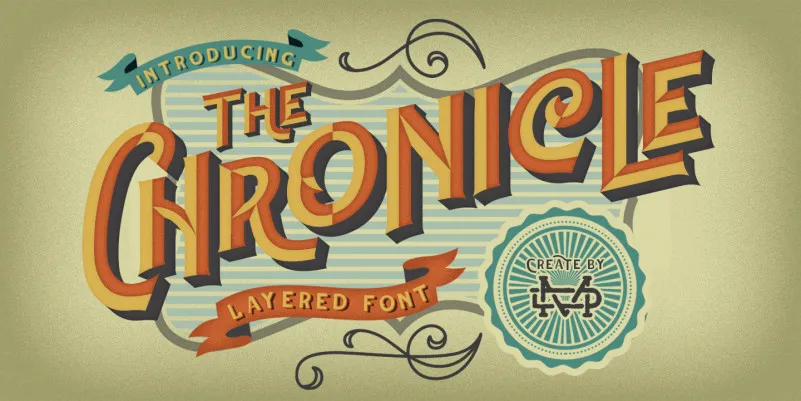
The Chronicle Layered Font – Download Grátis
A fonte ‘The Chronicle Layered Font’ é ideal para quem busca personalidade com estilo moderno. Seu design é perfeito para criações que exigem destaque e impacto, como posters de eventos, capas de livros, materiais de merchandising, campanhas de moda ou qualquer aplicação onde você deseja ressaltar sua mensagem de uma maneira única e emocionante. Seja para newsletter personalizadas, identidade visual, anúncios impressos, revistas, carteiras de convites, capas de álbuns ou até mesmo criações para levar o texto a um novo nível em citações especiais – The Chronicle é uma escolha ótima. Com suas variedades de gama do regular ao bold, você pode personalizar qualquer projeto para atender às necessidades específicas. Seja para criar capas memoráveis ou textos que se destacam na mídia impressa, certifique-se de usar o ‘The Chronicle Layered Font’ – sua criação vai ser um verdadeiro destaque.